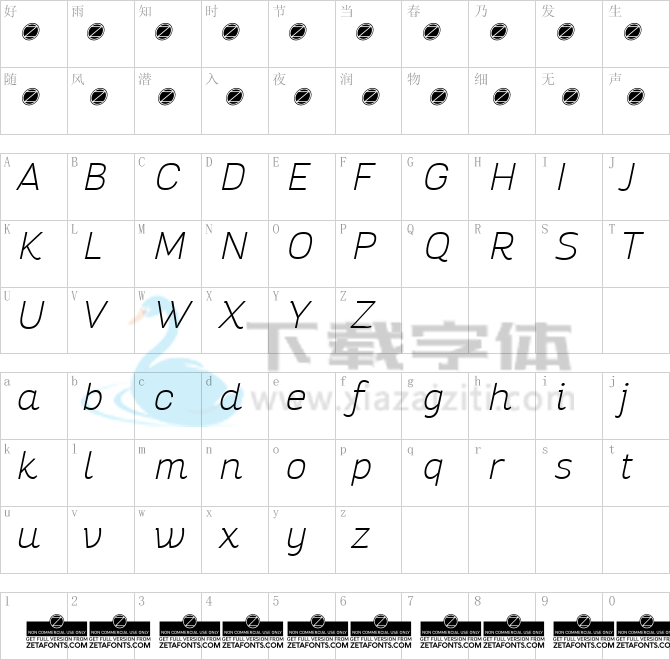
Altair Thin.ttf字体下载,这款字体结构工整、笔画清晰,兼顾美观与易读性,适用于标题、正文、海报、包装、LOGO 等多种场景。字形优雅稳定,风格百搭耐看,适配日常排版与创意设计,让文字呈现更舒适、更具质感。Altair Thin.ttf字体下载一笔一画,皆是细节,以均衡的比例、流畅的线条打造舒适视觉体验,字形端正大气,风格简约现代。无论是商业设计、品牌宣传还是日常排版,都能轻松驾驭,让文字更有格调与力量。Altair Thin.ttf字体下载字体下载。